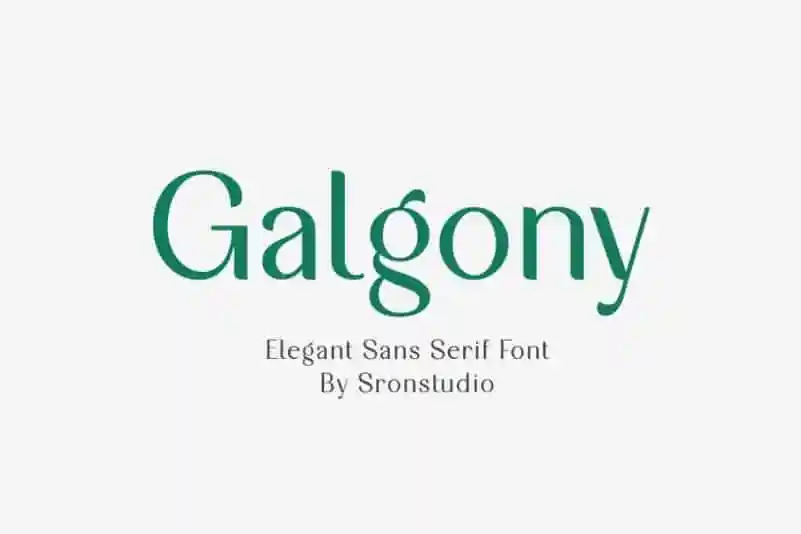
Galgony Sans Serif Font – Download Grátis
A Galgony Sans Serif Font é uma elegante e limpa tipografia sans serif que cativa os olhos desde a primeira impressão. Desenvolvida pela Sronstudio, essa fonte apresenta um contraste minimalista associado à moda há décadas. Ideal para diversos usos como identidade visual de empresas, convites, cartões postais, decoração nupcial, posts em redes sociais, anúncios e embalagens de produtos, além da fotografia e logotipia de eventos especiais. Suas linhas definidas oferecem um estilo limpo e moderno que se encaixa perfeitamente para estilos contemporâneos, permitindo que designers criem designs atraentes e profissionais em um amplo range de aplicativos. Experimente Galgony e deixe sua marca com um toque sofisticado e atualizado.